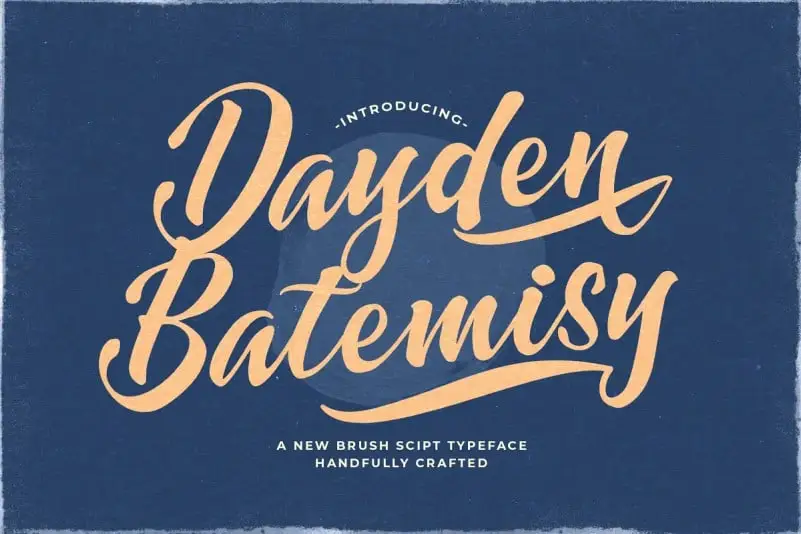
Dayden Batemisy Bold Script Font – Download Grátis
A fonte Dayden Batemisy Bold Script é uma moderna tipografia de calligrafia que incorpora variações básicas, linhas suaves e um toque clássico e elegante. Perfeita para designers visionários, essa fonte tem o poder de transformar qualquer design em algo único e imediatamente atrativo. Ideal tanto para logomarcas quanto para roupas customizadas ou embalagens de produtos, ela também é uma ótima escolha para textos de citações e embutir uma agilidade notável no tipo. Seja para qualquer projeto que precise de um pouco a mais de ênfase na tipografia, essa fonte é definitivamente o elemento desejado. Adquira-a hoje e deixe seu design brilhar ainda mais!